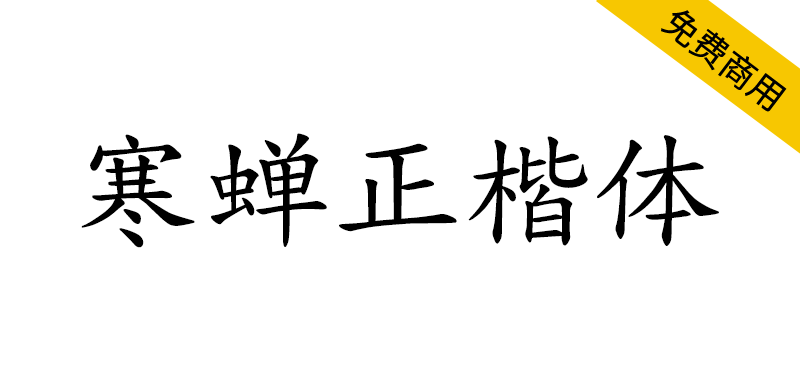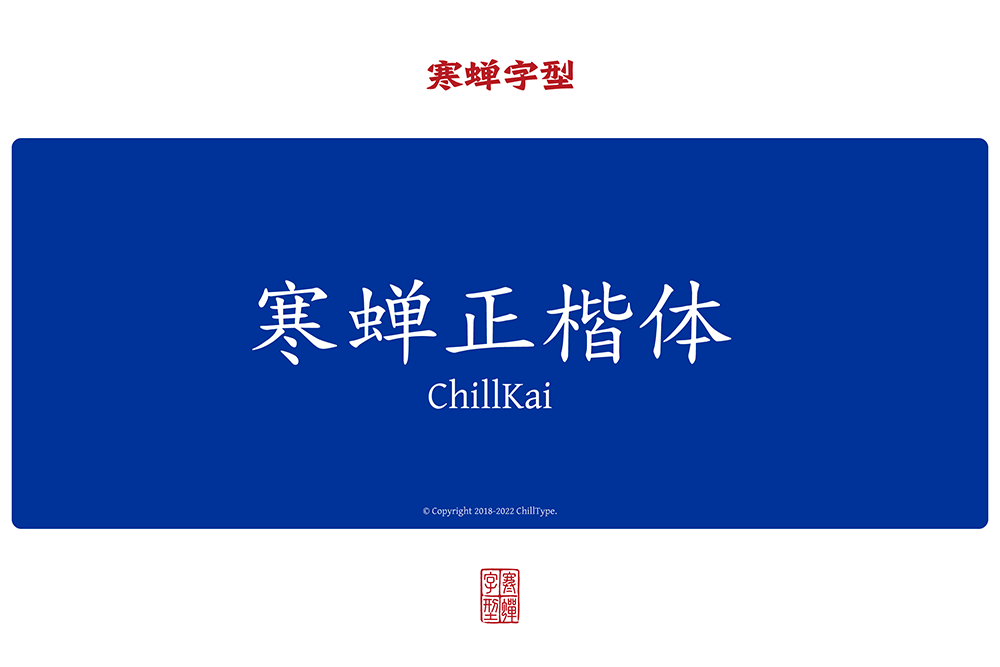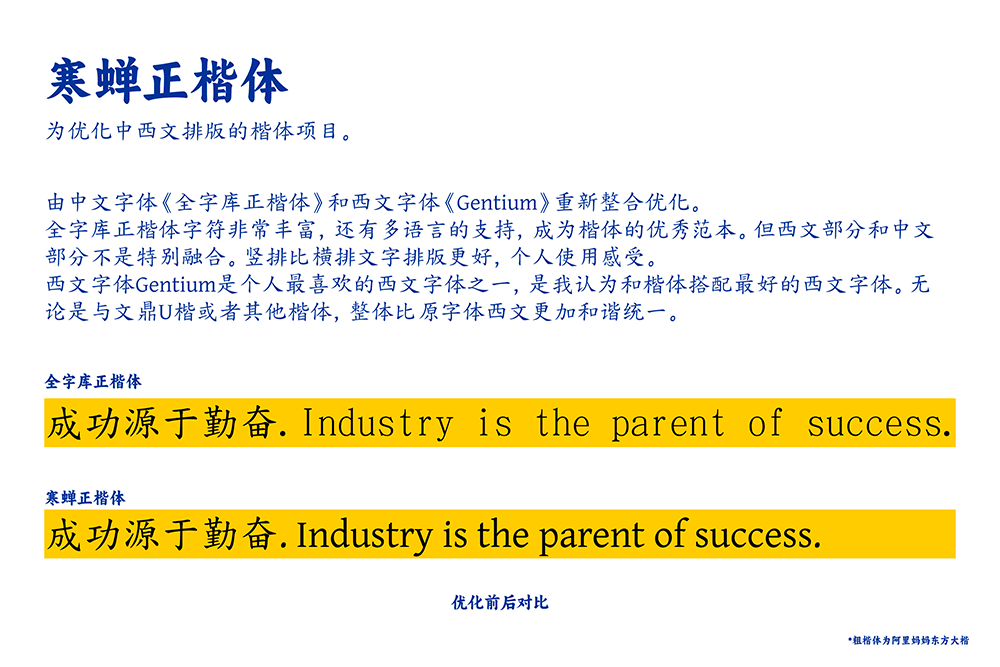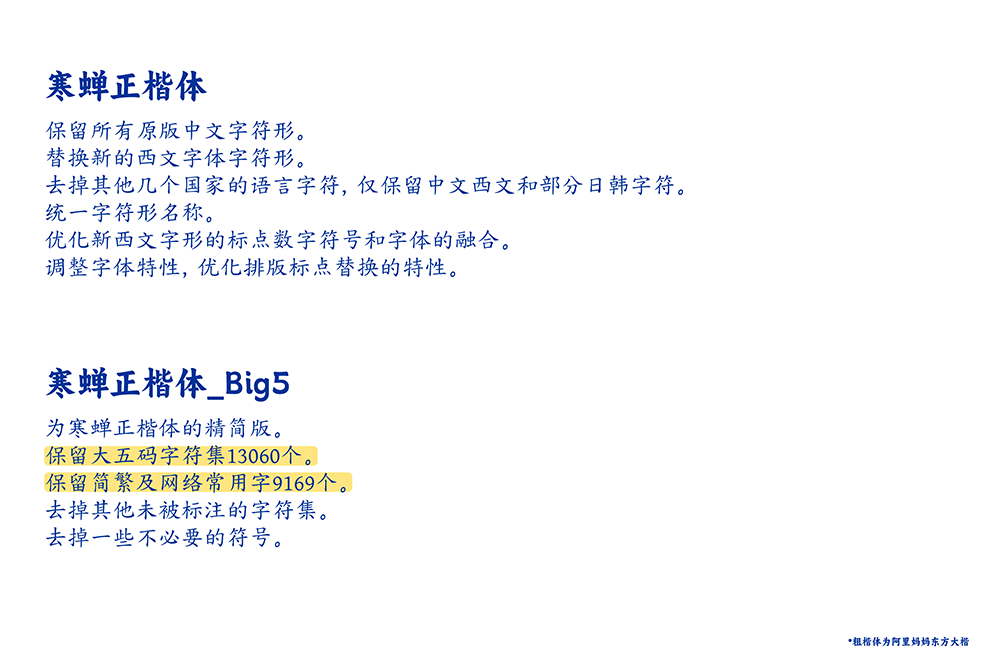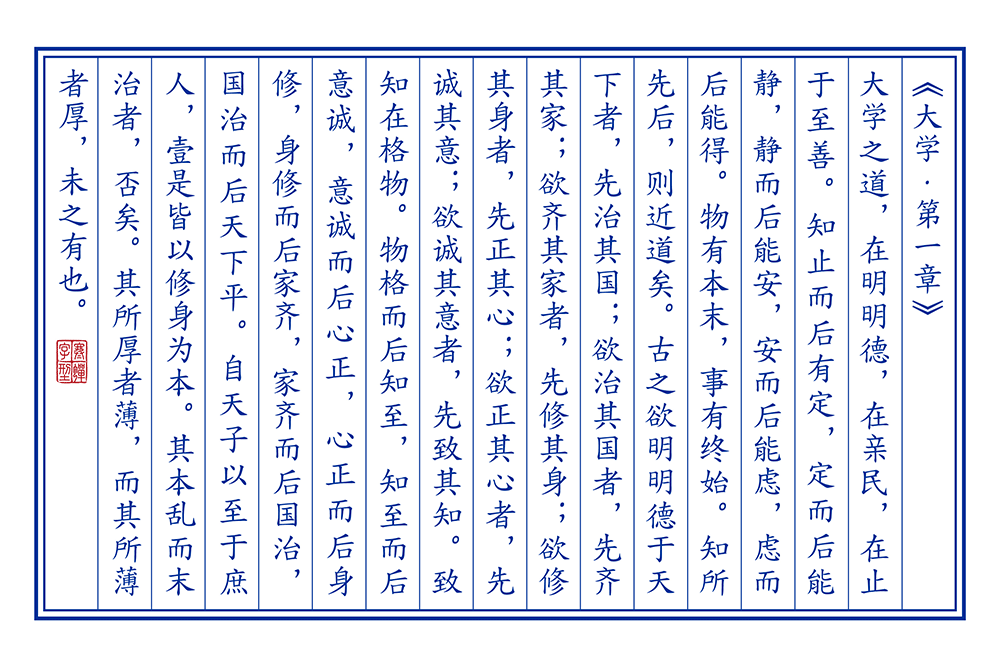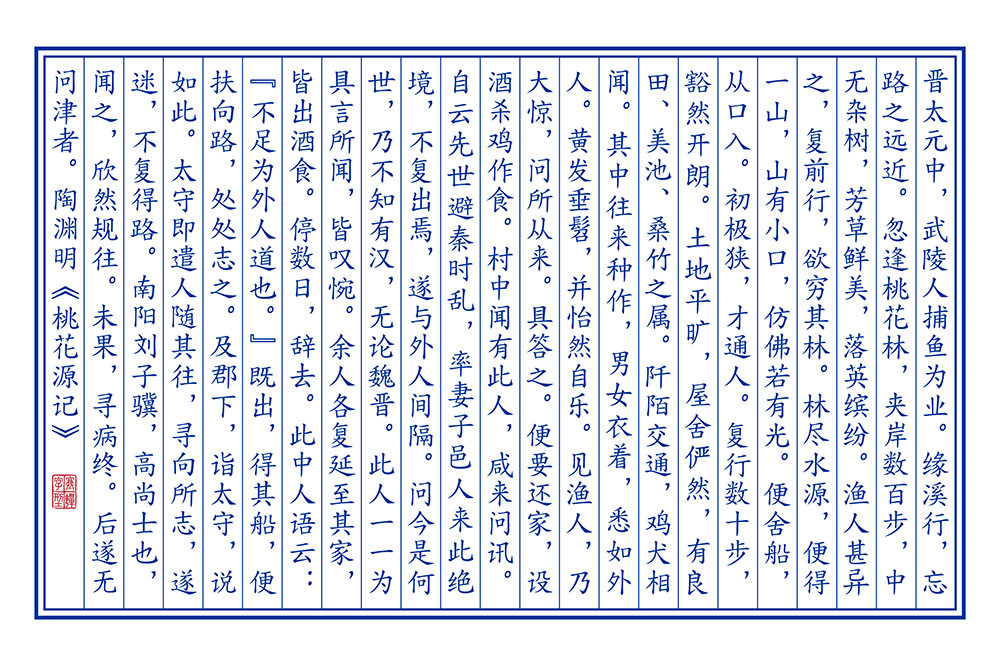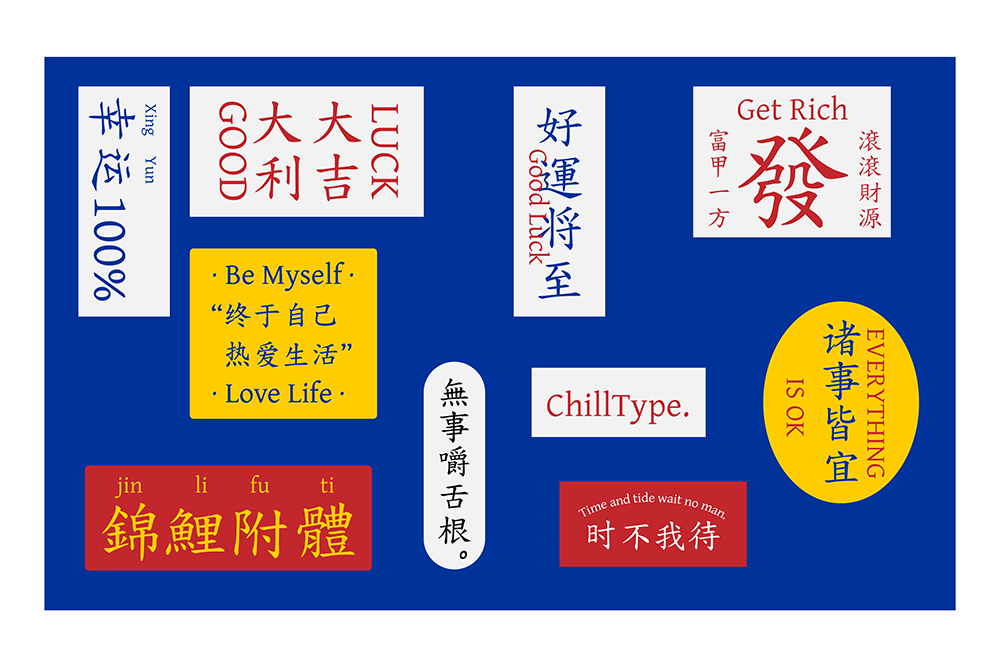
寒蝉正楷体(Chillkai)是一个为优化中西文排版的楷体项目,由中文字体《全字库正楷体》和西文字体《Gentium》重新整合优化。
全字库正楷体字符非常丰富,还有多语言的支持,成为楷体的优秀范本。但西文部分和中文部分不是特别融合。竖排比横排文字排版更好,个人使用感受。
西文部分Gentium是个人最喜欢的西文字体之一,是我认为和楷体搭配最好的西文字体。无论是与文鼎U楷或者其他楷体,整体比原字体西文更加和谐统一。